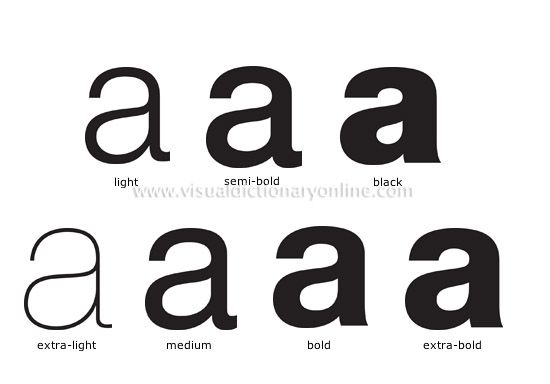
- Для класса
.page-titleзадайте шрифтовое семействоfont-familyсо значениемserif, - затем смените его на
sans-serif - а потом на
"Verdana", sans-serif.
CSS/Свойство font-family
Синтаксис
font-family: [[<название-семейства> | <общее-семейство>] [, [ <название-семейства> | <общее-семейство> ] ]* ] | inherit;
Описание
Свойство font-family указывает семейство шрифтов применяемое для отображения текста элемента. При этом в качестве одного пункта из списка значений может быть указано как какое-либо определённое семейство шрифтов, так и общее семейство шрифтов.
В CSS шрифты разбиваются на 5 общих семейств шрифтов:
- Общее семейство serif. Глифы шрифтов имеют засечки и, как правило, определённый интервал. Serif шрифты представляют собой «официальный» стиль текста и часто используются в официальных документах. Примеры семейств шрифтов: «Constantia», «Times New Roman», «Liberation Serif», «Droid Serif», «Century Schoolbook L», «FreeSerif», «Linux Libertine G», «Nimbus Roman No9 L». Символы с засечками и без
- Общее семейство sans-serif. Глифы шрифтов имеют низкую контрастность и простые штриховые окончания. Как правило, имеют определённый интервал. Примеры семейств шрифтов: «Droid Sans», «FreeSans», «Nimbus Sans L».
- Общее семейство cursive. Используется более неформальный стиль письменности. Текст выводимый с помощью таких шрифтов больше похож на надпись сделанную ручкой или кистью.
Примеры семейств шрифтов: «Antonella script», «Monplesir script», «Rigoletto», «Alexandra Script», «Bickham Script Two», «Burlak», «Liana», «Aquarelle». - Общее семейство fantasy. Включает в себя декоративные или выразительные шрифты, которые содержат выразительные или экспрессивные символы. (Они не включают в себя Pi или Picture шрифты, которые не имеют реальных символов.) Примеры семейств шрифтов: «Aurora», «CRYSIS», «Impact», «Masquerade», «Arnold BocklinC», «Benny Blanco», «elektrodisiac», «Epilog», «Crystal», «Wenatchee», «Young Love ES», «NERVOUS».
Свойства шрифта
| Недвижимость | Описание | Значения |
|---|---|---|
| шрифт | Задает все свойства шрифта в одном объявлении | стиль шрифта, вариант шрифта, вес шрифта, размер шрифта/высота строки, семейство шрифтов, подпись, значок, меню, окно сообщения, маленький заголовок, статус бар, унаследовать |
| семейство шрифтов | Указывает семейство шрифтов для текста | фамилия, родовое семейство, унаследовать |